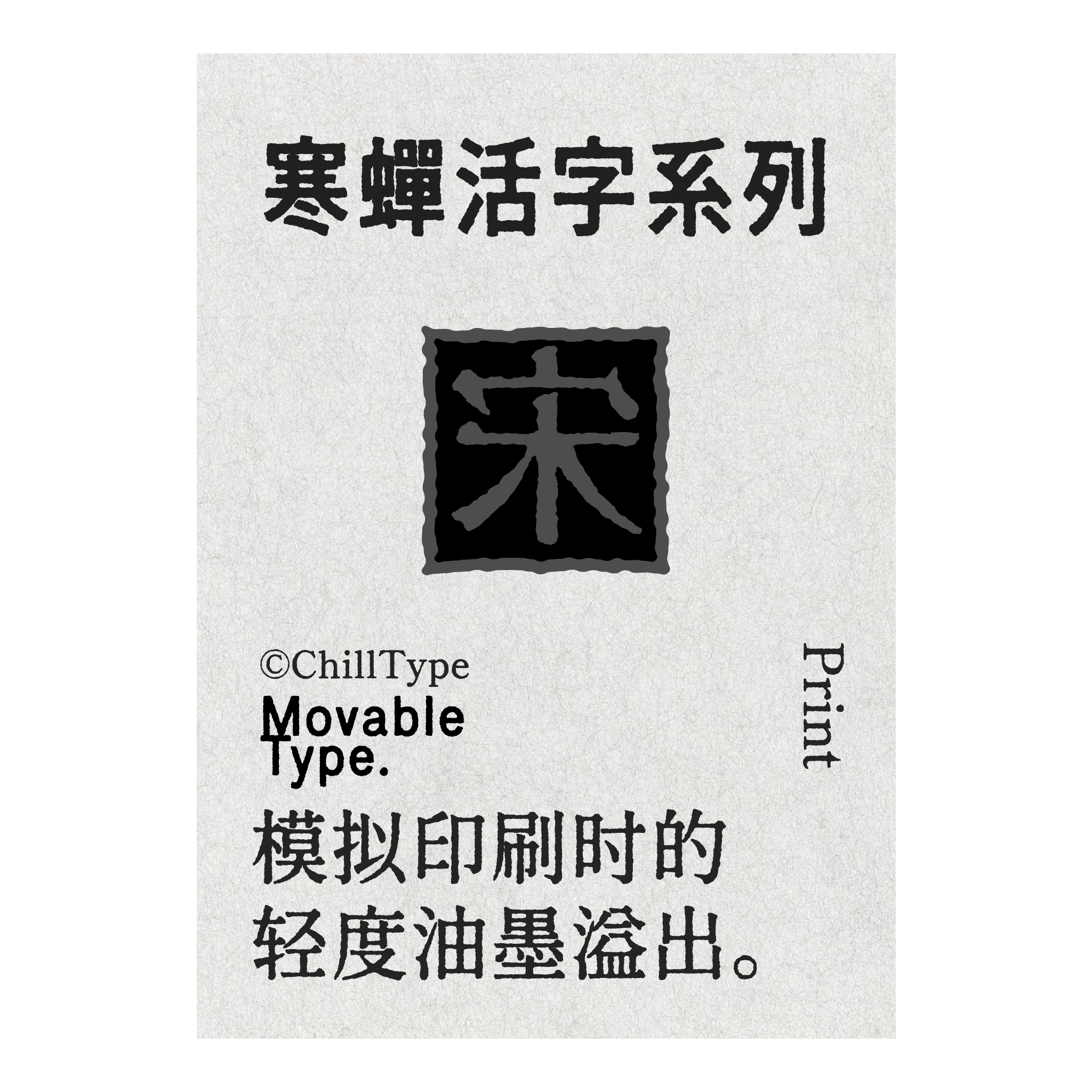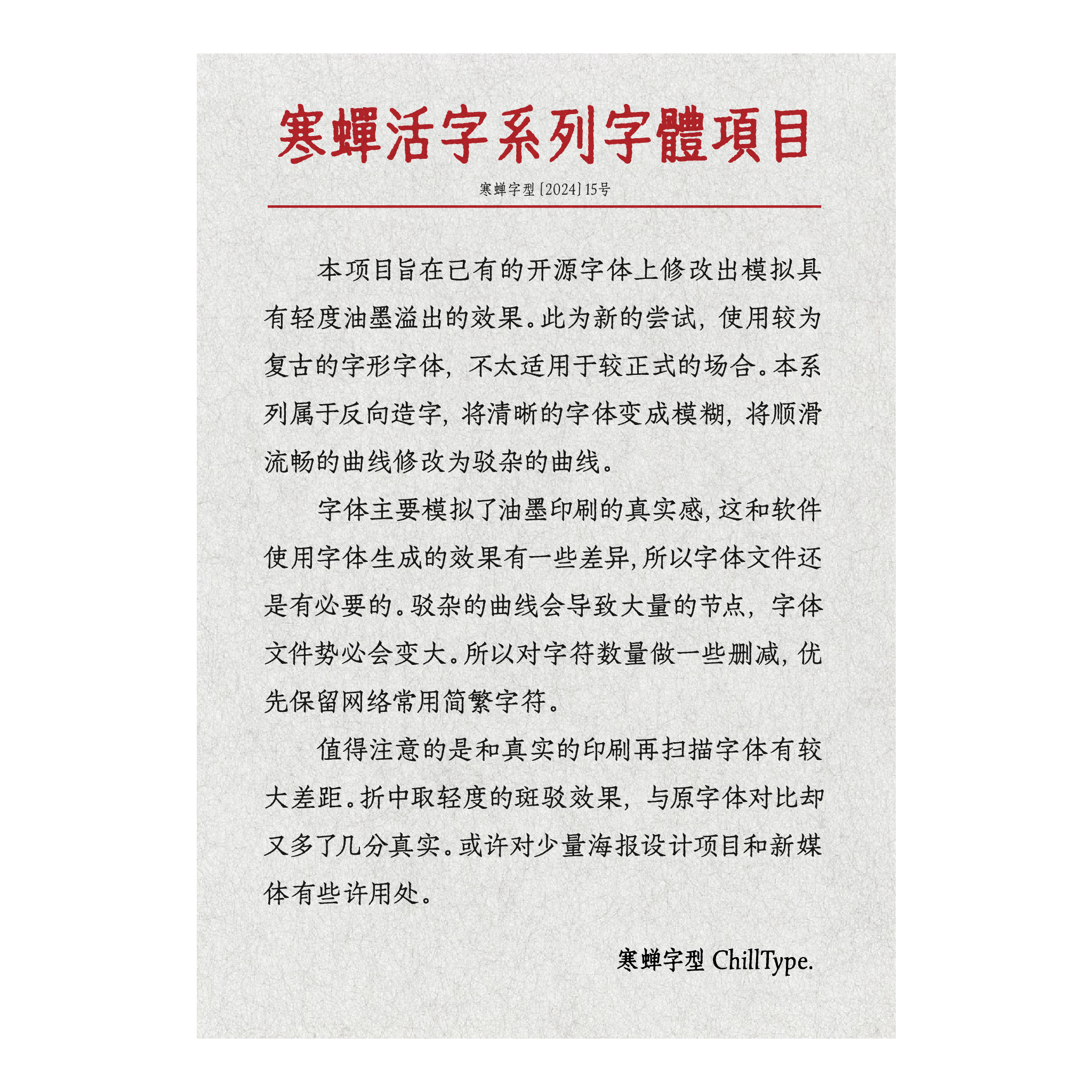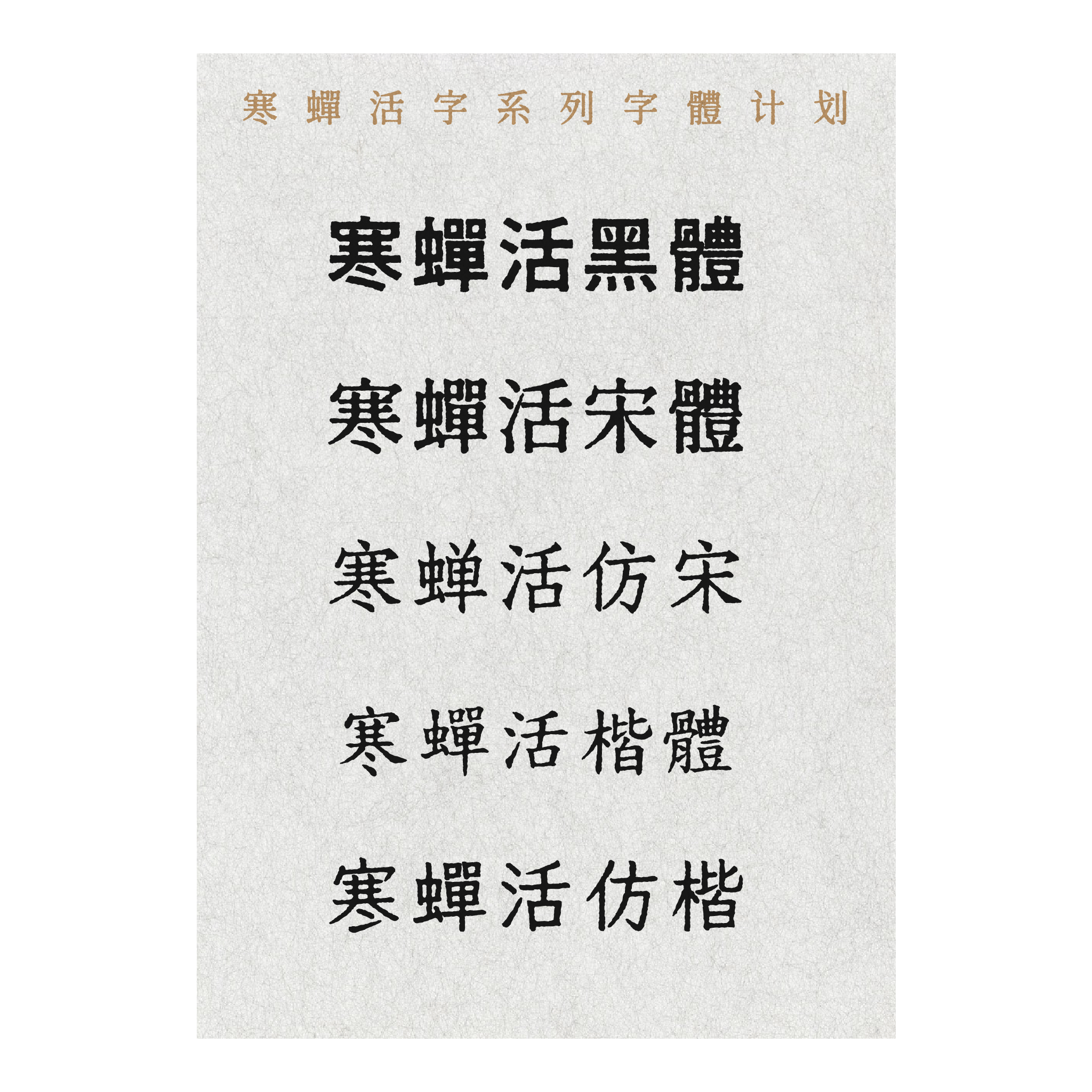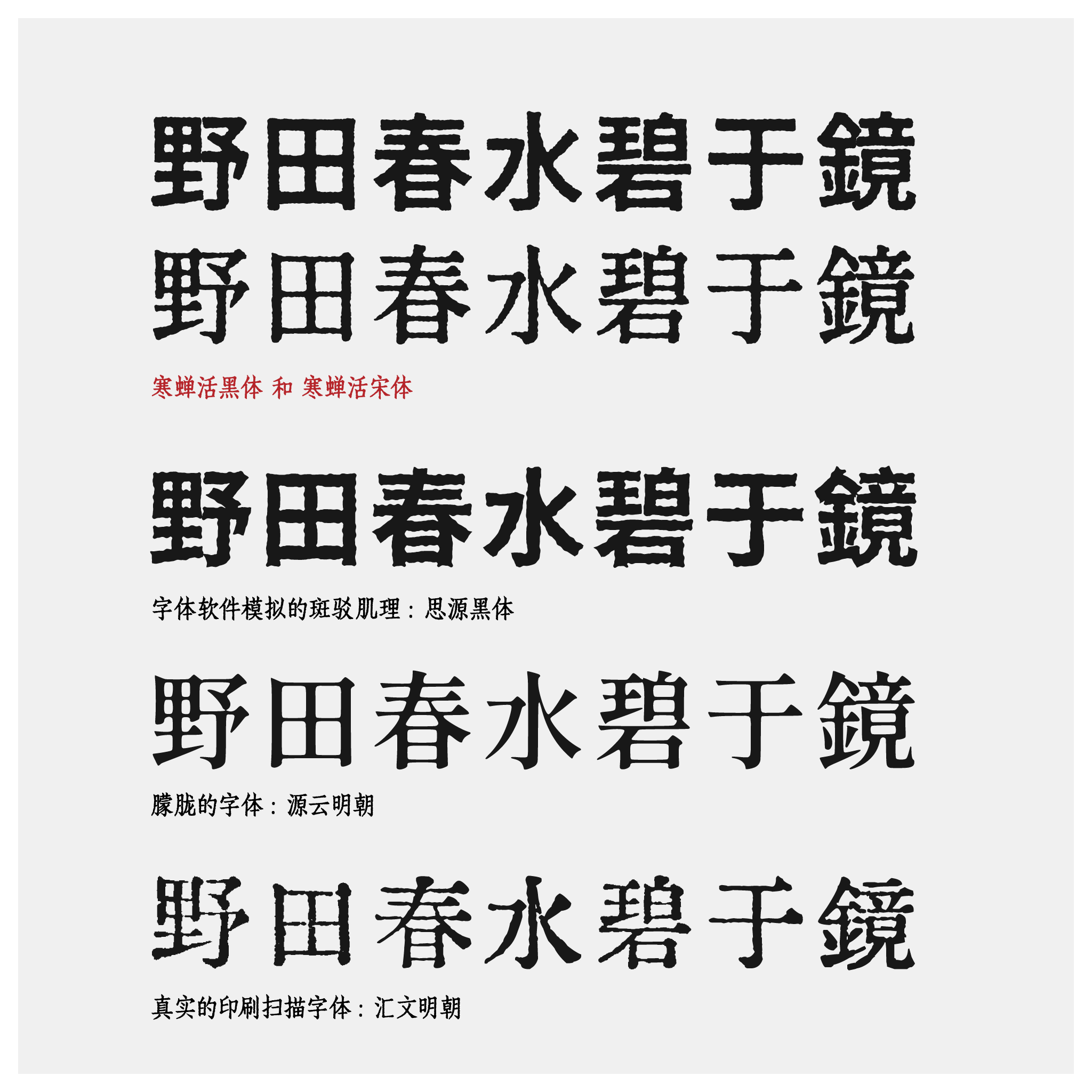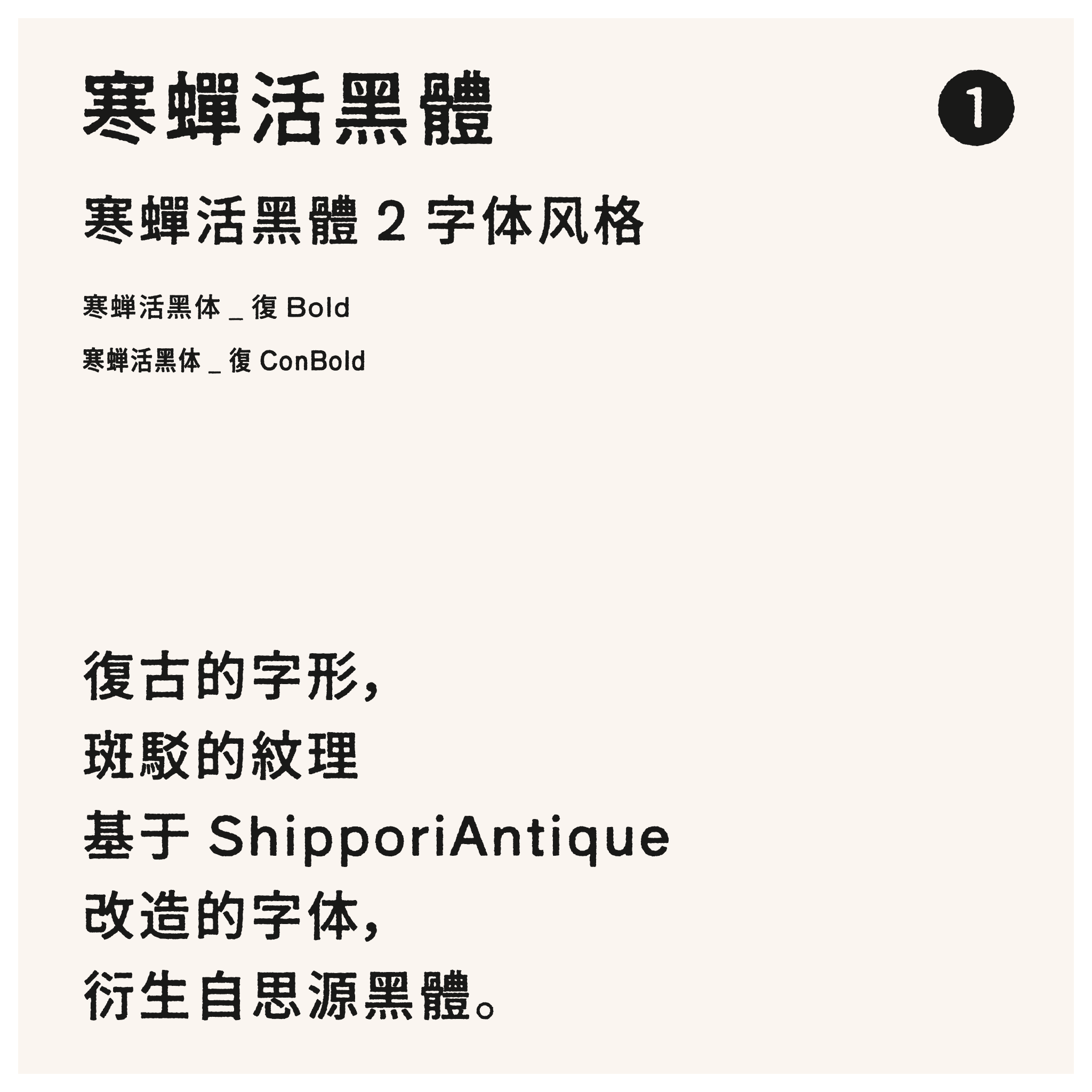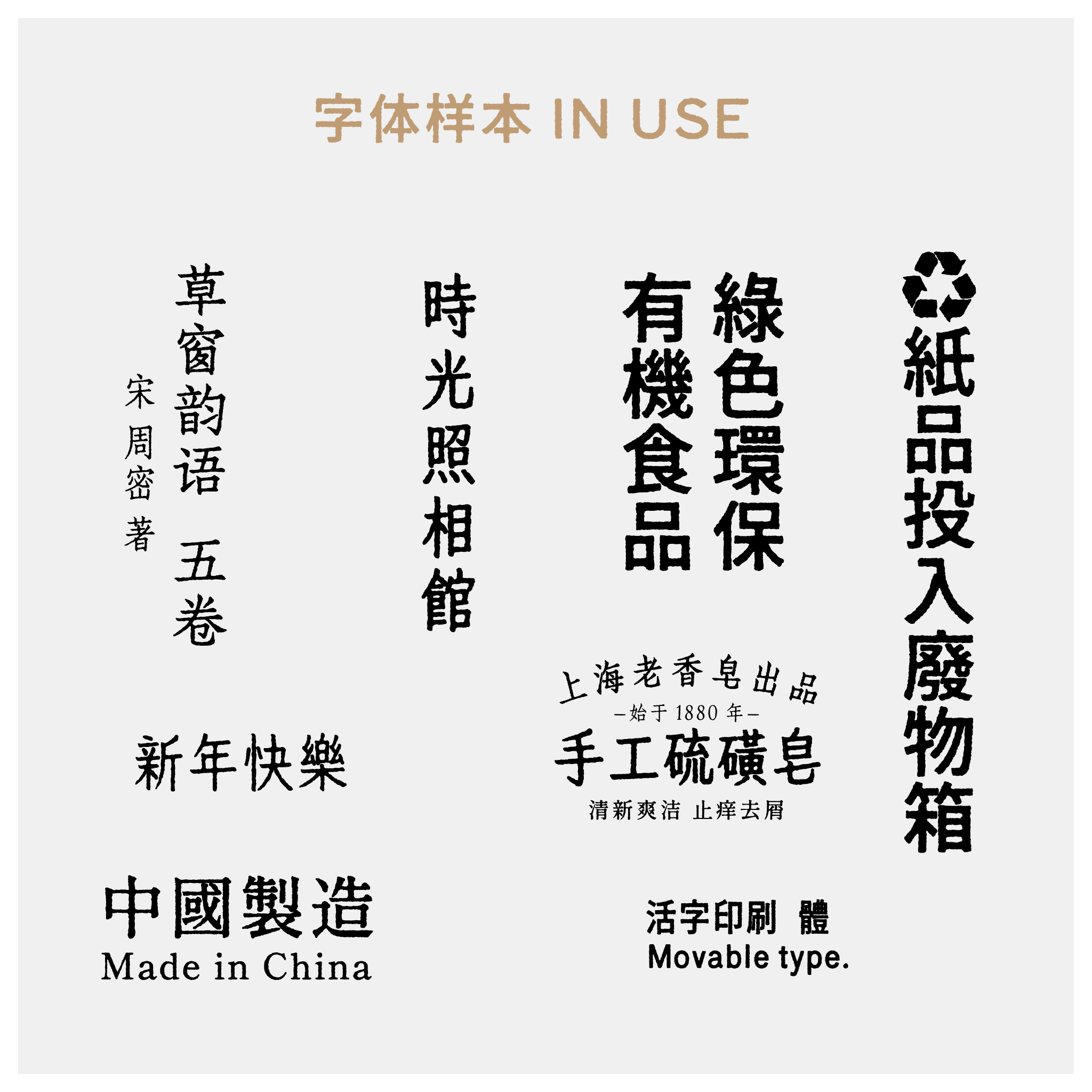
寒蝉活黑体 是一款具有浓郁復古韵味的字体,其设计灵感源自传统的活字印刷美学。字形结构上,它保留了早期印刷品的严谨与稳重,同时通过现代化的重新设计,使其更适应屏幕阅读和当代排版需求。字体的纹理处理尤为特别,采用了模拟斑驳、磨损效果的设计,仿佛历经岁月洗礼,每一道细微的裂痕与褪色都精心复刻,增添了视觉上的历史层次感与独特个性。这款字体衍生自广受好评的开源思源黑體,并在这一坚实基础上,融合了 Shippori Antique 字体的复古基因。Shippori Antique 本身以其优雅的古典风格和细腻的细节著称,寒蝉活黑体借鉴了其装饰性元素与形态韵律,并将其与思源黑體清晰易读的骨架相结合,最终形成了一款兼具艺术表现力与实用性的特色字型,非常适合用于标题、品牌标识、艺术设计以及任何需要强调传统、手工或复古氛围的场景。